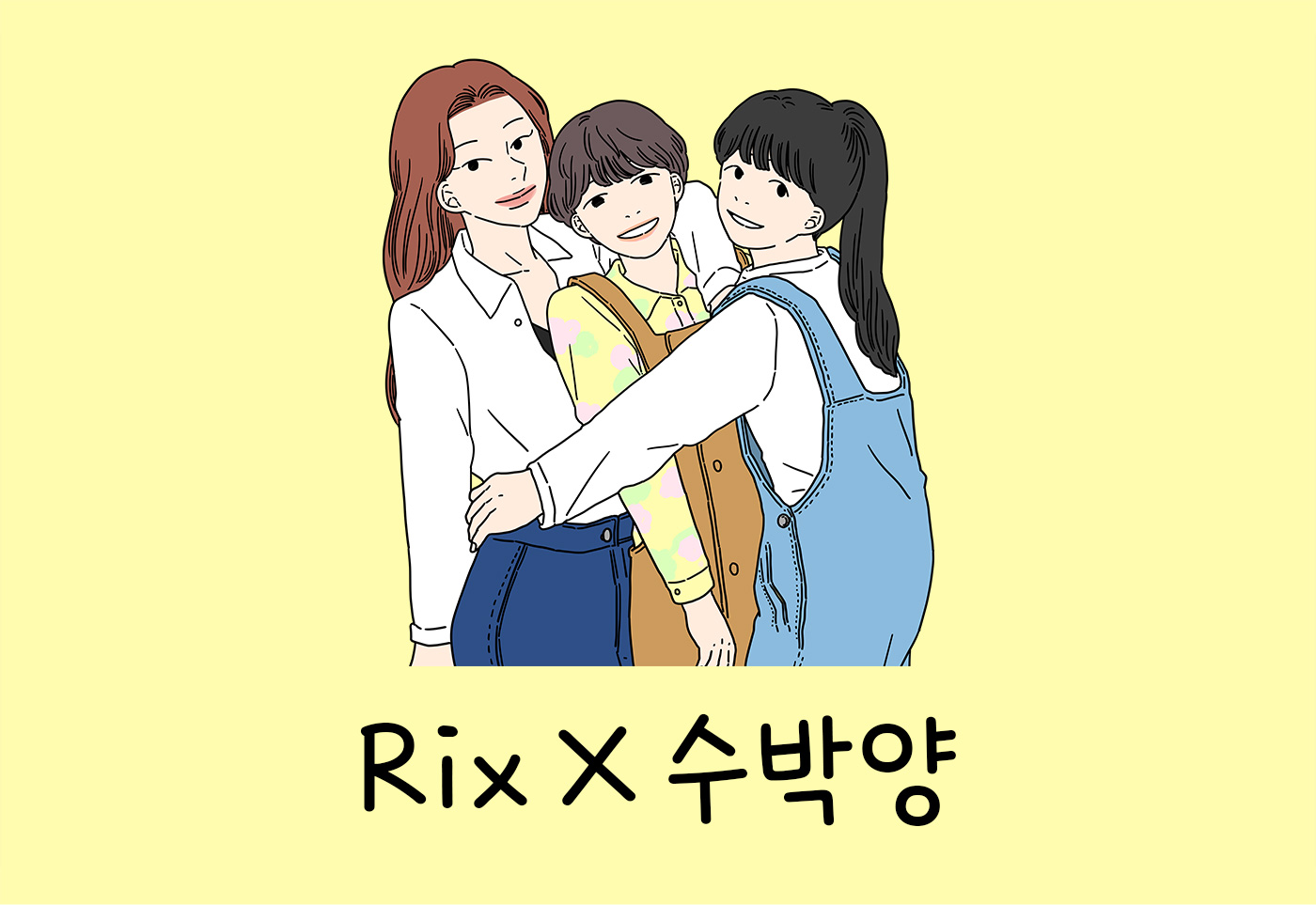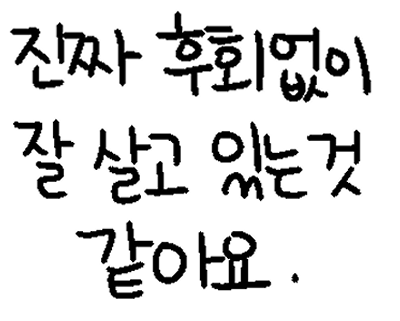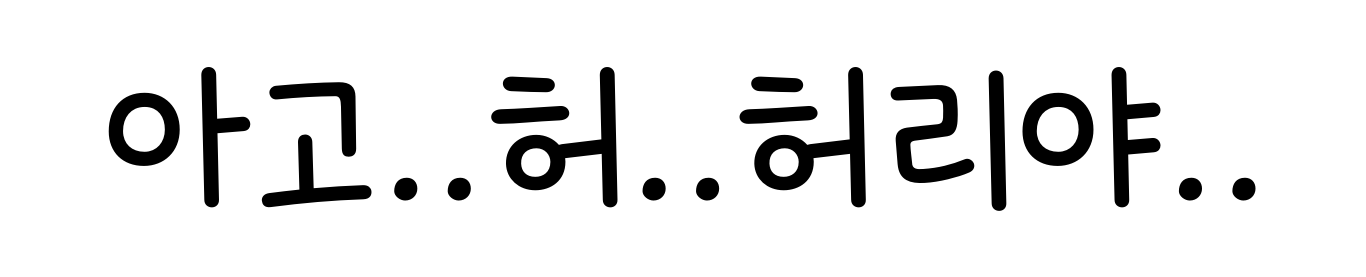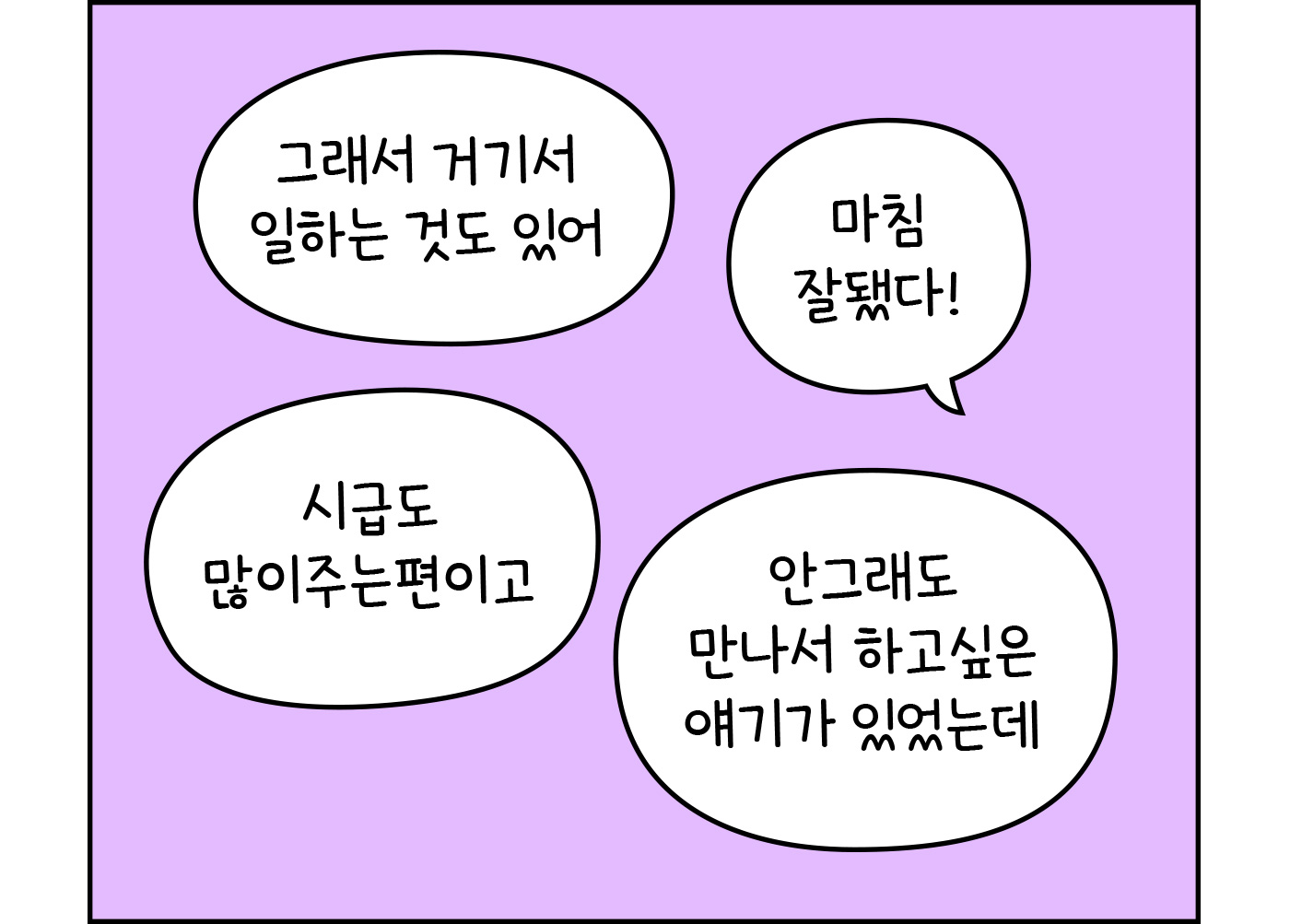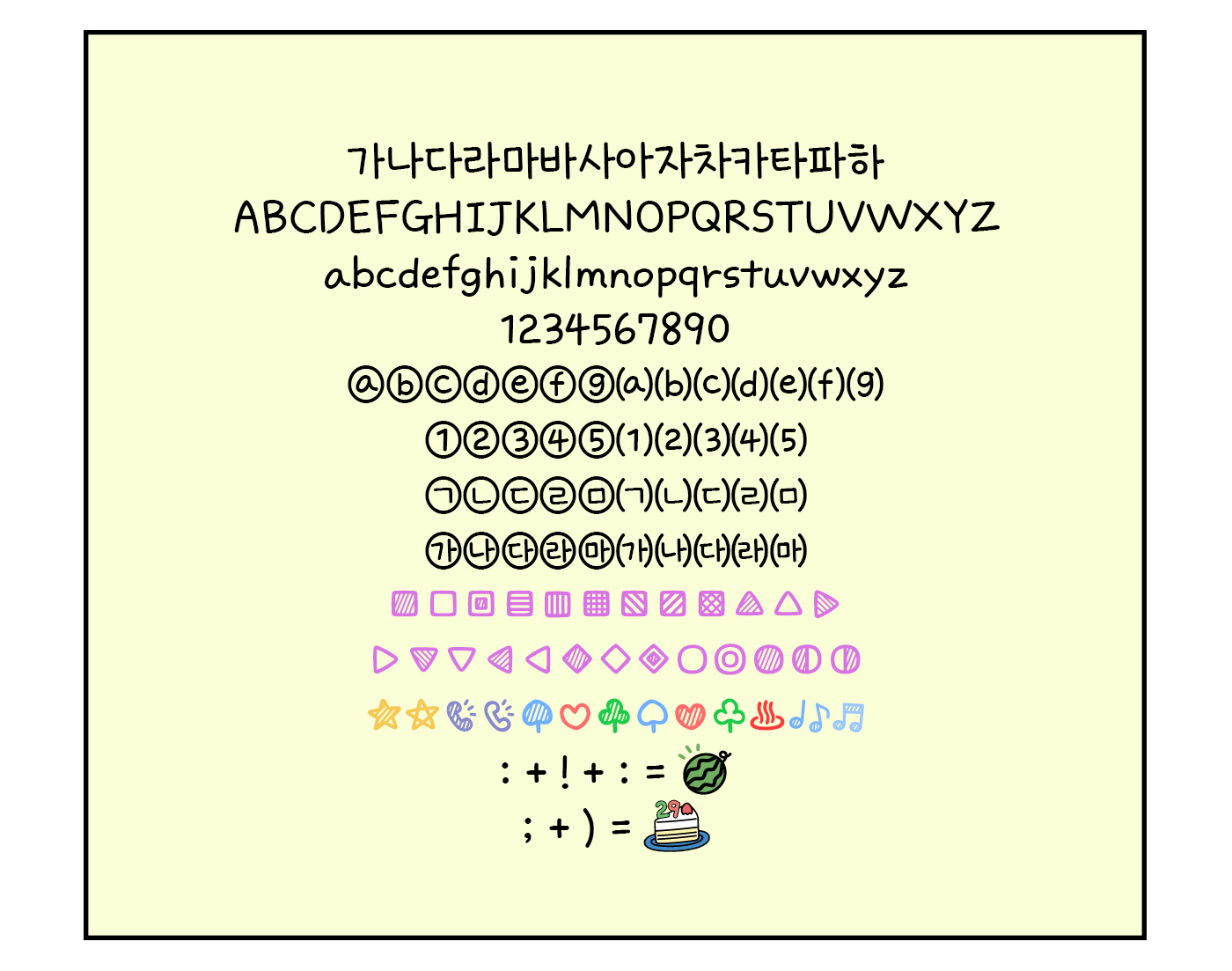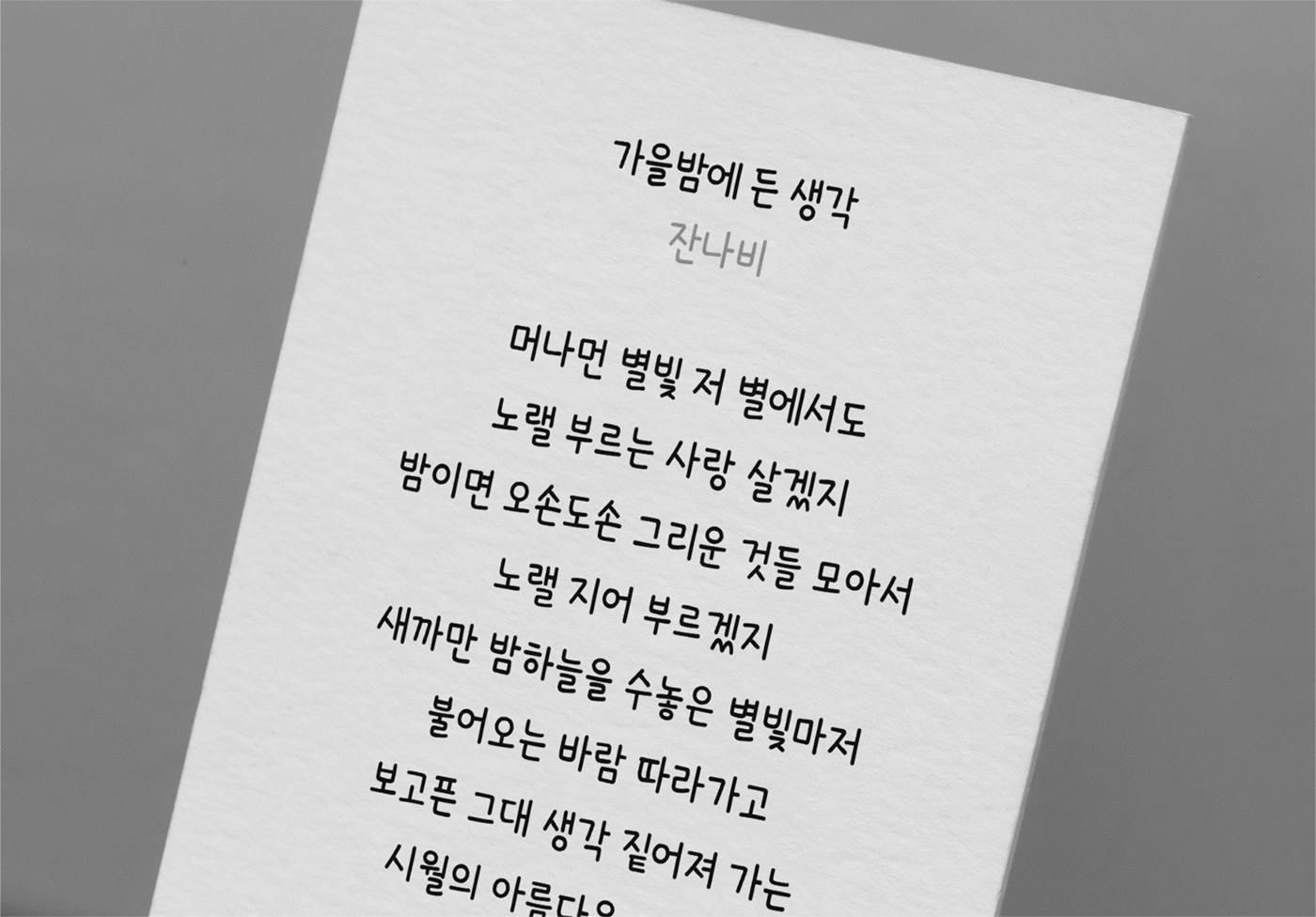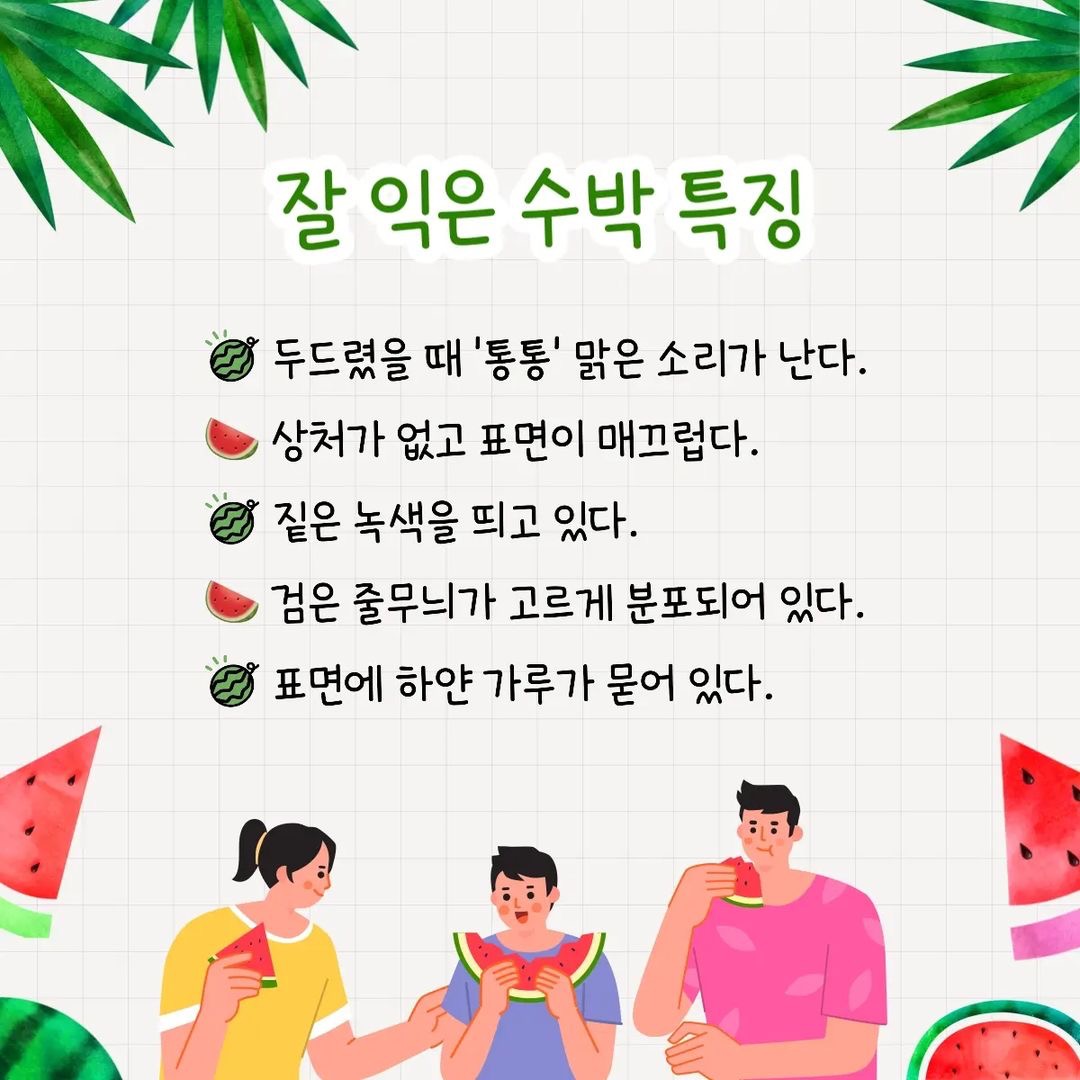
안녕하세요. 이번 11월에는 조금 특별한 서체를 소개하게 되었습니다. 바로 웹툰 <아홉수 우리들>의 수박양 작가님과 콜라보로 제작한 「Rix X 수박양」폰트입니다! 수박양 작가님의 웹툰 속 손글씨를 바탕으로 구현한 손맛이 느껴지는 귀여운 폰트인데요, 폰트 제작을 맡은 박민우 디자이너와의 인터뷰를 통해 자세히 알아보겠습니다 :)
안녕하세요, 박민우 디자이너님. 이번 서체는 조금 특별한 폰트라고 들었어요!
안녕하세요! 이번 폰트는 네이버 웹툰 “아홉수 우리들”의 수박양 작가님과의 콜라보로 탄생한 폰트입니다. 웹툰 “아홉수 우리들”의 말풍선 속 대사를 통해 만날 수 있었던 작가님의 매력적인 손글씨를 한글 11,172자 완전 지원 폰트로 제작하게 되었습니다.
작가의 손글씨를 바탕으로 제작한 콜라보 폰트인 만큼 어떤 프로세스를 거쳤는지 궁금해요.
작가님이 직접 적으신 대사 psd 파일을 자본으로 전달받아 한 글자씩 분리한 뒤, 모임꼴 별로 달라지는 획의 구조를 파악했습니다. 그 후 작가님의 손글씨 골격에 맞춰 기본 글자를 만들고, 이후 확장 글자를 파생해 11,172자의 폰트 한 벌을 완성했습니다!
아무래도 0에서 시작한 폰트가 아니다 보니 또 다른 의미로 신경 쓸 부분이 많았을텐데 어땠나요?
폰트의 컨셉과 세부적인 디자인을 창조해 내야 하는 작업은 아니었지만, 이미 있는 손글씨를 폰트화하는 작업이다 보니 작가님의 개성과 자소의 특징을 살리면서 한 벌의 폰트로서의 균일한 표정을 유지하는 일에 신경을 많이 썼습니다. 손글씨이기 때문에 하나의 자소의 형태가 같은 꼴에서도 다르게 나타난다거나, 글줄이 오르락내리락하는 경우가 있었는데요, 모임꼴에 따라 어울리는 자소 모양을 적용해 통일시키고 글줄 가운데로 시각 흐름을 맞추되 약간의 변주를 주는 식으로 폰트화 작업을 진행했습니다.
이번 신서체를 준비하면서 느낀 점이 있다면?
이전에 작업했던 힘찬 느낌의 폰트들과는 달리 가벼운 느낌의 손글씨 폰트라서 그런지, 딱딱한 폰트 디자인에 압도되는 느낌 없이 편안하게 제작할 수 있었습니다. 또박또박 적은 캐주얼한 손글씨가 어울릴 만한 곳에서 자주 만났으면 좋겠어요!
폰트 디자이너로 일을 한다는 것은 어떤가요?
개인적인 성향과 잘 맞는 것 같아요! 폰트 디자인은 한 프로젝트의 호흡이 비교적 길고 반복 작업이 많아 일견 지루해 보일 수 있지만, 다른 디자인 작업물 대비 결과물의 생명력이 길다는 것이 매력이에요. 잘 만들어진 폰트는 십 년, 이십 년을 넘어 기백 년을 살아남는 힘을 가지고 있어요. 저는 아직 그런 폰트를 잘 만들지 못하지만, 그런 힘을 가진 단단한 폰트를 제작하는 것이 꿈입니다!
정감 가는 손글씨의 맛
아홉수에 제대로 걸린 2030의 로맨스를 재밌게 풀어낸 네이버 웹툰 '아홉수 우리들'
Rix X 수박양 폰트는 작가의 이름을 그대로 폰트명에 넣은 서체인 만큼, <아홉수 우리들>이라는 웹툰으로 큰 히트를 친 수박양 작가의 원본 손글씨를 최대한 살려 제작했습니다. 아마 작품을 보신 분들이라면 이 손맛이 느껴지는 귀여운 글씨체가 눈에 띄었을텐데요!
폰트에서도 손글씨의 동글동글한 'ㅇ'꼴과 쌍시옷의 독특한 모양을 특징으로 그대로 살려 구현했습니다.
영문, 숫자, 특수 기호 등에도 폰트 스타일을 적용한 디자인으로 귀여움이 한가득! 이질감 없이 한글과 함께 사용할 수 있고, 리가처 기능을 지원하여 귀여운 딩벳들도 있으니 꼭 써보시길 바라요🍉
이렇게 활용해 보세요👀
친근한 이미지를 주는 손글씨 스타일의 폰트라 어디든 쉽게 어울린다는 장점이 있어요. 짧은 글, 영상 자막, 카드 뉴스 등 다양하게 활용해 보세요!
11,172자 한글 지원의 위엄..! 모든 글자를 쓸 수 있도록 풀패키지로 제작했으니 외계어도 자유롭게 써보세요👽